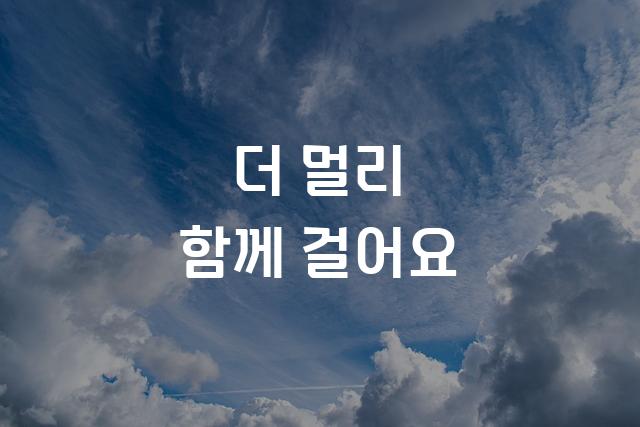
엘리스 디지털코딩체는 세련된 둥근 고딕 디자인과 코딩에 최적화된 글꼴로, 디지털 환경에서의 가독성과 편안함을 제공합니다. 이 폰트는 현대적 감성과 기술적 요구를 모두 충족시키는 이상적인 선택입니다.
엘리스 디지털코딩체은(는)
기본 고딕, 둥근 스타일, 픽셀/코딩, 감성적인, 게임 느낌, 부드러움, 복실복실 계열의 생김새를 가지고 있으며
웹/앱 디자인, 브랜딩, 보고서/문서 등에서 자주 활용되며, 효과적인 메시지 전달에 적합합니다.
이 폰트는 크리에이티브, 기술/IT, 금융/비즈니스 분야에 잘 어울리며,
명확한, 창의적인, 전문적인 느낌을 담고 있는 것이 특징입니다.